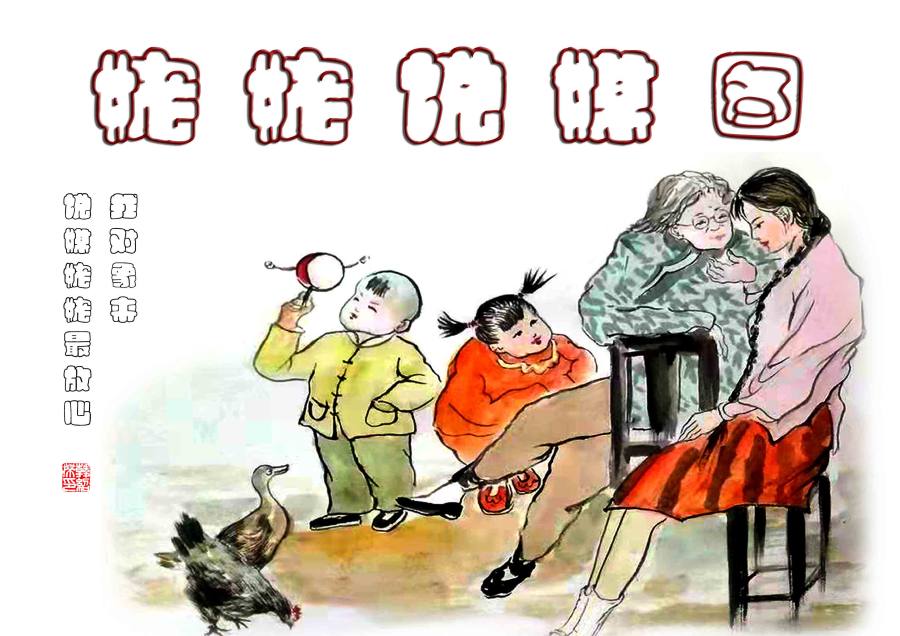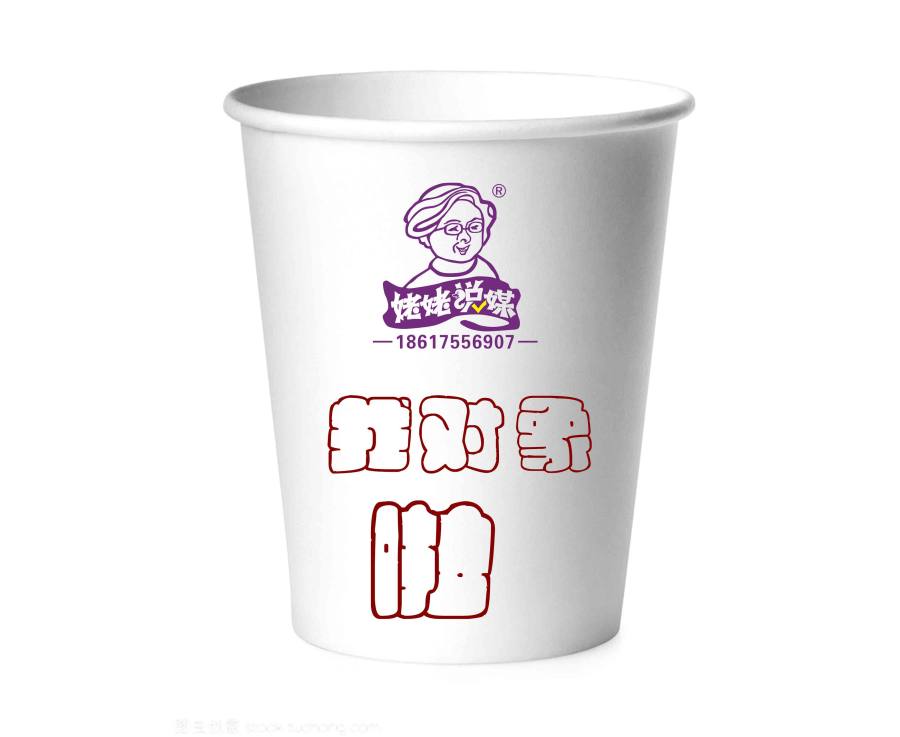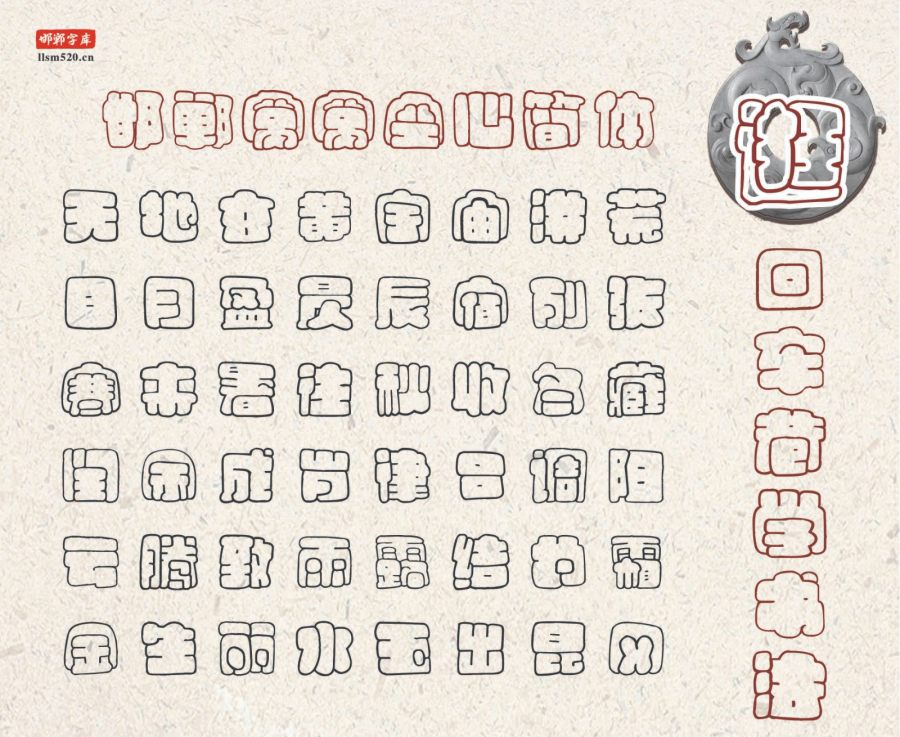
邯郸窝窝空心简体笔画粗壮,两端呈圆头,笔画相交紧密,呈凹陷窝状,中宫比较紧凑。黑字面大,字型粗旷,结构严谨,重心一致;内心空心,外轮廓描边,别具儿童风格;笔划制作精良,线条刚柔相济,简洁有力。阅读舒适流畅,适用于报刊、杂志和书籍中的大型标题。
邯郸窝窝空心简体,笔画粗状、横竖清晰、内心空心,外轮廓描边,别具儿童风格;突出醒目等特点, 有着非常强烈的现代感。